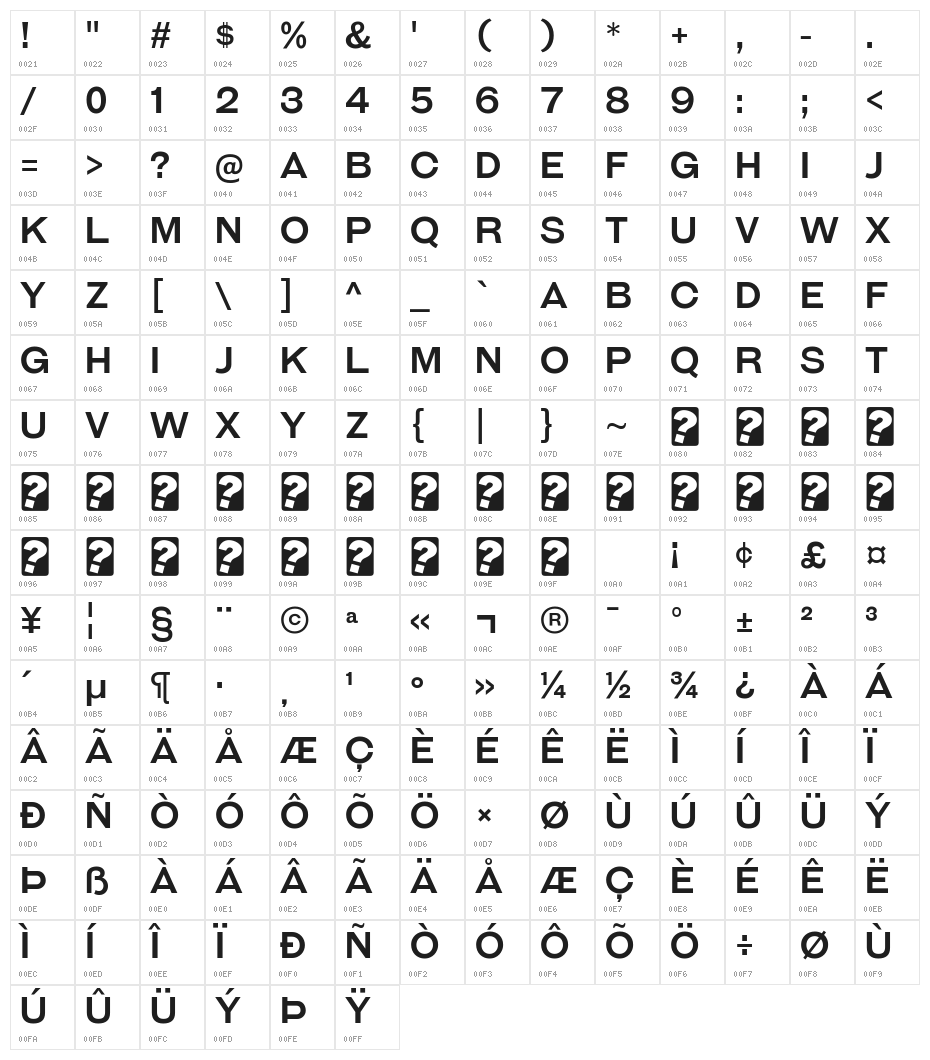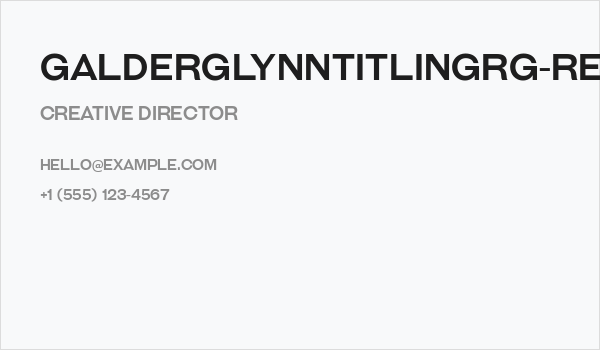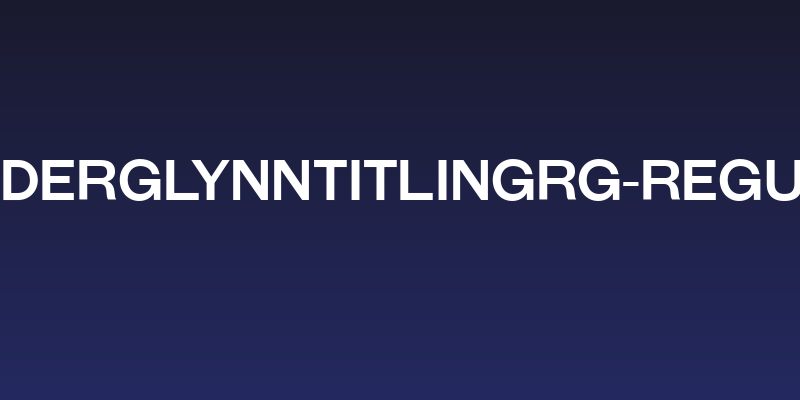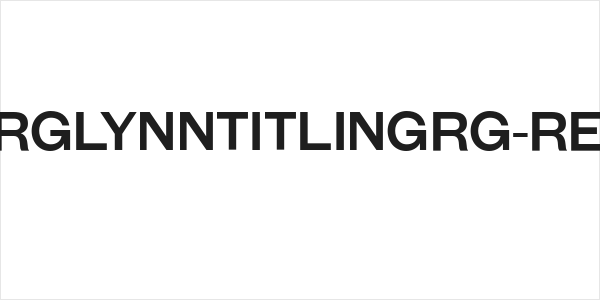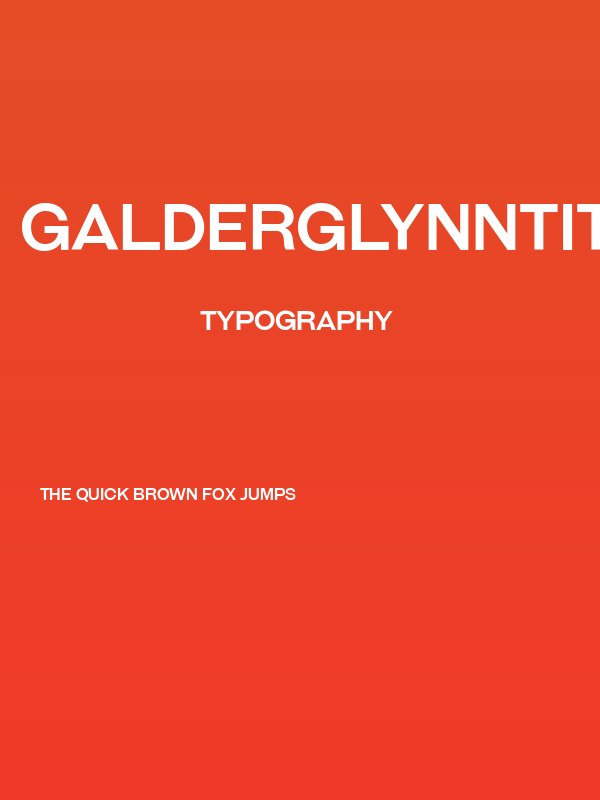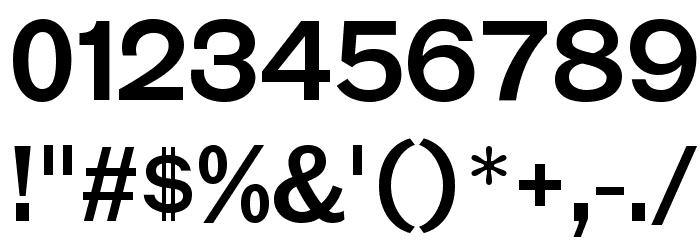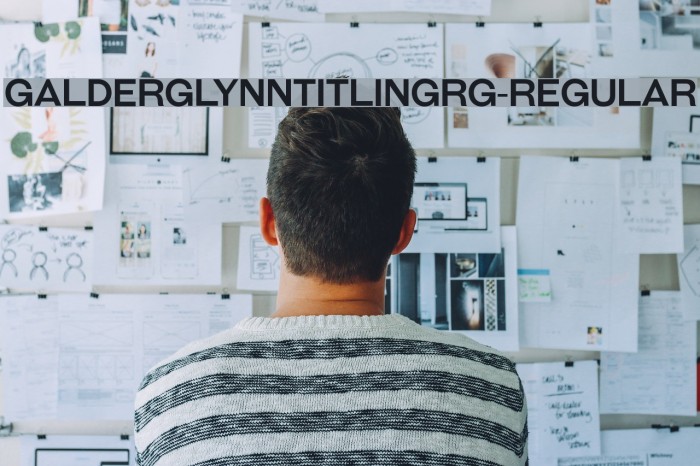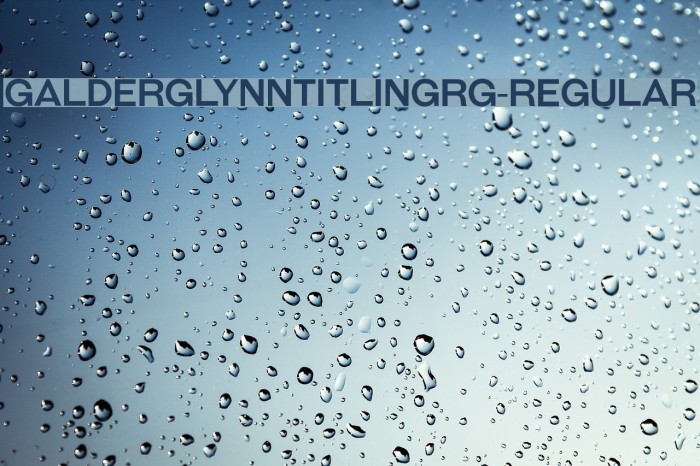
GalderglynnTitlingRg-Regular Font
Typodermic Fonts - Ray Larabie - www.typodermicfonts.com/
| Familia de fuentes | Galderglynn Titling Rg |
| Categorías | Sans Serif |
| Caso de uso | Headlines, Logos, Branding |
| Proyectos propuestos | Ideal for branding, advertising, headlines, and digital media projects requiring a modern and professional look. |
| Autor | Typodermic Fonts - Ray Larabie - www.typodermicfonts.com/ |